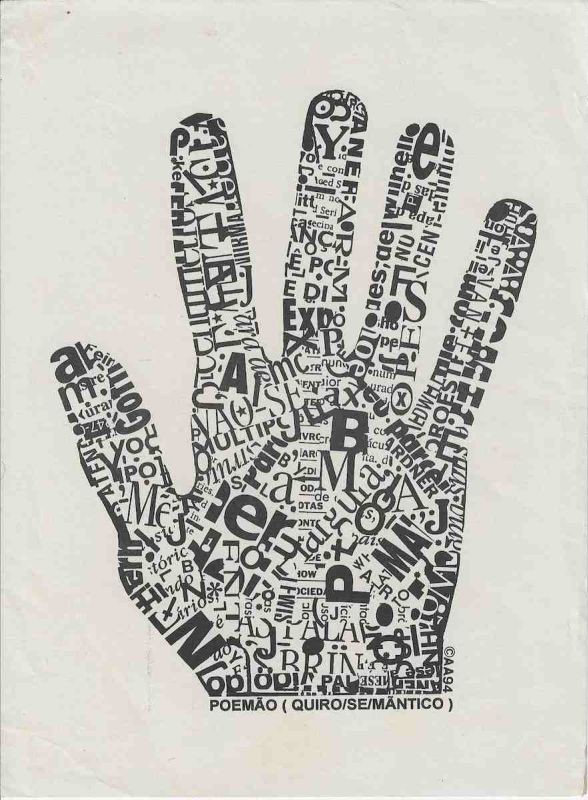
Poemão Quiro Semântico é uma impressão gráfica de Avelino de Araújo realizada em 1994, vinculada à poesia visual, à poesia experimental, à arte conceitual, à tipografia e às investigações intersígnicas relacionadas ao campo do Poema Processo.
Poemão Quiro Semântico é uma impressão gráfica de Avelino de Araújo realizada em 1994, vinculada à poesia visual, à poesia experimental, à arte conceitual, à tipografia e às investigações intersígnicas relacionadas ao campo do Poema Processo. A composição apresenta a silhueta de uma mão aberta construída integralmente por letras, palavras, fragmentos de textos, números, sinais de pontuação e caracteres tipográficos de diferentes tamanhos, pesos e orientações. O título registrado na base da obra aparece como POEMÃO QUIRO SEMÂNTICO e estabelece um jogo entre poema, mão, linguagem e produção de sentido. O termo Poemão pode indicar um poema de grandes dimensões e também aproxima sonoramente as palavras poema e mão. O elemento Quiro deriva de uma raiz associada à mão, presente em palavras relacionadas à leitura manual, ao gesto e à atividade realizada pelas mãos. Semântico refere se aos significados produzidos e transmitidos pela linguagem. A reunião desses elementos define a imagem como uma mão formada por sentidos, palavras e sinais. Avelino de Araújo transforma a anatomia humana em campo textual e demonstra que a escrita pode adquirir corpo, contorno e presença física. A mão aparece como instrumento de criação, trabalho, comunicação, escrita, leitura, toque, identidade e ação. As palavras ocupam a palma e os cinco dedos, adaptando seus tamanhos e direções aos limites da silhueta. Alguns caracteres são ampliados e funcionam como pontos de intensidade visual, enquanto outros aparecem comprimidos, sobrepostos ou fragmentados. O observador reconhece inicialmente a forma da mão e, em seguida, percebe a multiplicidade de conteúdos verbais que constroem sua superfície. Essa alternância entre leitura global e leitura dos detalhes aproxima a obra dos princípios da poesia visual e da comunicação não linear. Os fragmentos textuais não formam necessariamente uma mensagem contínua e podem ser compreendidos como memória gráfica, repertório linguístico, acumulação cultural ou fluxo de informações. A mão também pode sugerir impressão digital ampliada, mapa do conhecimento, arquivo corporal ou retrato sem rosto. Cada palavra participa da imagem ao mesmo tempo como signo verbal e como matéria visual. A obra investiga as relações entre corpo e linguagem, gesto e significado, escrita e imagem, forma e conteúdo, indivíduo e coletividade. O contraste entre preto e fundo claro reforça a definição da mão e intensifica a diversidade interna dos caracteres. Na base aparecem a identificação POEMÃO QUIRO SEMÂNTICO, a marca de autoria A A e a indicação 94, correspondente ao ano de 1994. Poemão Quiro Semântico integra a produção de Avelino de Araújo dedicada à transformação de palavras, sinais tipográficos, imagens corporais e sistemas de comunicação em poemas visuais abertos à participação interpretativa do observador. Palavras chave para indexação: Avelino de Araújo, Poemão Quiro Semântico, Poemao Quiro Semantico, 1994, impressão gráfica, poesia visual brasileira, poema visual, poesia experimental, arte conceitual, Poema Processo, mão tipográfica, mão formada por palavras, corpo e linguagem, tipografia experimental, escrita visual, palavra imagem, texto imagem, letras, números, sinais gráficos, semântica, quiro, gesto, comunicação, identidade, criação artística, semiótica, intersigno, leitura não linear, arte gráfica brasileira, múltiplo gráfico, arquivo de poesia visual, arte brasileira do século vinte.TEXT FOR THE SALSA PROGRAM IN ENGLISH: Poemão Quiro Semântico is a graphic print by Avelino de Araújo produced in 1994 and associated with visual poetry, experimental poetry, conceptual art, typography and intersemiotic investigations related to the field of the Poema Processo movement. The composition presents the silhouette of an open hand constructed entirely from letters, words, fragments of texts, numbers, punctuation marks and typographic characters of different sizes, weights and orientations. The title recorded at the bottom appears as POEMÃO QUIRO SEMÂNTICO and establishes a wordplay involving poem, hand, language and the production of meaning. The term Poemão may indicate a large poem and also creates a phonetic relationship between the Portuguese words poema and mão, meaning poem and hand. The element Quiro derives from a root associated with the hand and with manual action, gesture and interpretation through the hand. Semântico refers to the meanings produced and transmitted by language. Together these elements define the image as a hand formed from meanings, words and signs. Avelino de Araújo transforms human anatomy into a textual field and demonstrates that writing may acquire body, contour and physical presence. The hand functions as an instrument of creation, labor, communication, writing, reading, touch, identity and action. Words occupy the palm and the five fingers, adapting their dimensions and directions to the boundaries of the silhouette. Some characters are enlarged and function as points of visual intensity, while others appear compressed, superimposed or fragmented. The viewer initially recognizes the form of the hand and then perceives the multiplicity of verbal content constructing its surface. This alternation between global recognition and detailed reading connects the work with the principles of visual poetry and nonlinear communication. The textual fragments do not necessarily form a continuous message and may be understood as graphic memory, linguistic repertoire, cultural accumulation or a flow of information. The hand may also suggest an enlarged fingerprint, a map of knowledge, a bodily archive or a portrait without a face. Each word participates in the image simultaneously as a verbal sign and as visual material. The work investigates relationships between body and language, gesture and meaning, writing and image, form and content, individuality and collectivity. The contrast between black and the light background reinforces the definition of the hand and intensifies the internal diversity of the characters. The lower section contains the identification POEMÃO QUIRO SEMÂNTICO, the authorship mark A A and the indication 94, corresponding to the year 1994. Poemão Quiro Semântico belongs to Avelino de Araújo
Impressão gráfica em tinta preta sobre papel claro, composta pela silhueta de uma mão aberta orientada verticalmente e ocupando a maior parte da região central da folha. A palma, o polegar e os quatro dedos são preenchidos por grande quantidade de letras, palavras, sílabas, números e sinais tipográficos. Os caracteres apresentam diferentes fontes, tamanhos, espessuras e direções. Algumas palavras aparecem horizontalmente, outras verticalmente, inclinadas, invertidas ou parcialmente sobrepostas. As áreas mais largas da palma concentram letras maiores e maior densidade de informação. Nos dedos, os elementos são comprimidos e adaptados ao formato estreito e alongado. O contorno da mão é produzido exclusivamente pela disposição dos caracteres, sem necessidade de uma linha externa contínua. Na margem inferior aparece a inscrição POEMÃO QUIRO SEMÂNTICO em letras maiúsculas, enquanto a marca de autoria A A 94 está posicionada junto à lateral direita da base da mão. O suporte apresenta ondulações, vincos, marcas de dobra, pequenas manchas, alterações de tonalidade e sinais de envelhecimento e manuseio. A peça pode ser classificada como poema visual, impressão de artista, múltiplo gráfico, composição tipográfica, imagem corporal, colagem verbal e documento conceitual, sendo relevante para pesquisas sobre Avelino de Araújo, Poema Processo, poesia visual, mão, corpo, linguagem, tipografia, semântica, semiótica e produção gráfica brasileira.OBSERVATION TEXT IN ENGLISH: Graphic print in black ink on light colored paper composed of the silhouette of an open hand positioned vertically and occupying most of the central region of the sheet. The palm, thumb and four fingers are filled with a large quantity of letters, words, syllables, numbers and typographic signs. The characters present different typefaces, sizes, thicknesses and directions. Some words appear horizontally, while others are vertical, inclined, inverted or partially superimposed. The wider areas of the palm contain larger letters and greater informational density. In the fingers, the elements are compressed and adapted to the narrow elongated forms. The outline of the hand is created exclusively through the arrangement of the characters without the need for a continuous external line. The lower margin contains the inscription POEMÃO QUIRO SEMÂNTICO in capital letters, while the authorship mark A A 94 appears beside the lower right area of the hand. The support presents undulations, creases, fold marks, small stains, changes in tone and signs of aging and handling. The piece may be classified as a visual poem, artist print, graphic multiple, typographic composition, bodily image, verbal collage and conceptual document, making it relevant to research on Avelino de Araújo, Poema Processo, visual poetry, the hand, the body, language, typography, semantics, semiotics and Brazilian graphic production.
Poemão Quiro Semântico is a graphic print by Avelino de Araújo produced in 1994 and associated with visual poetry, experimental poetry, conceptual art, typography and intersemiotic investigations related to the field of the Poema Processo movement.